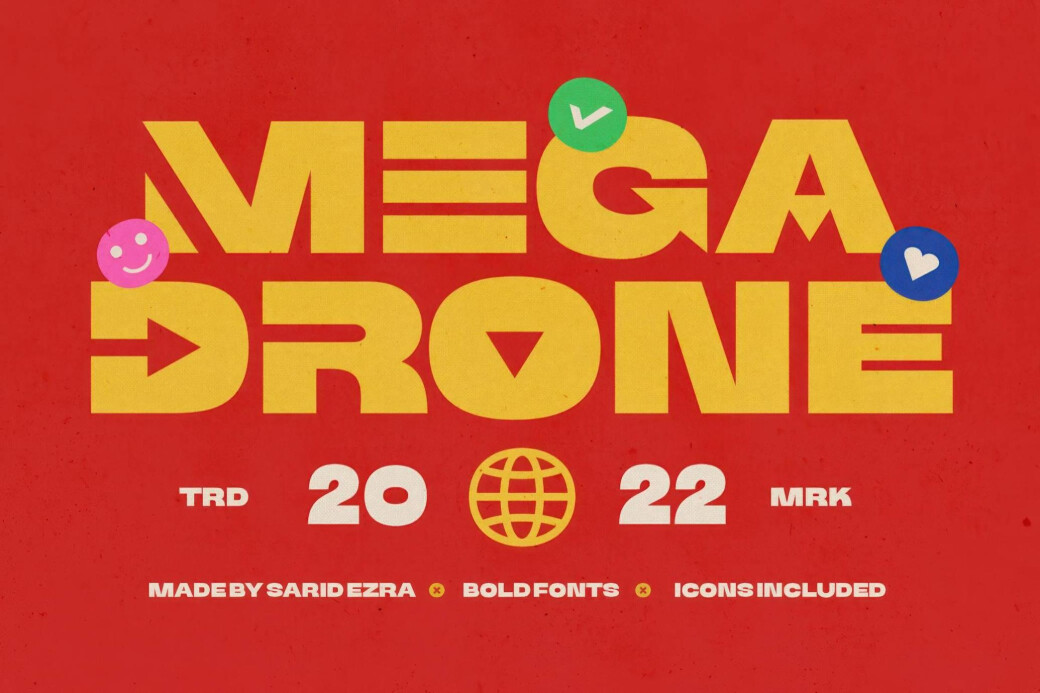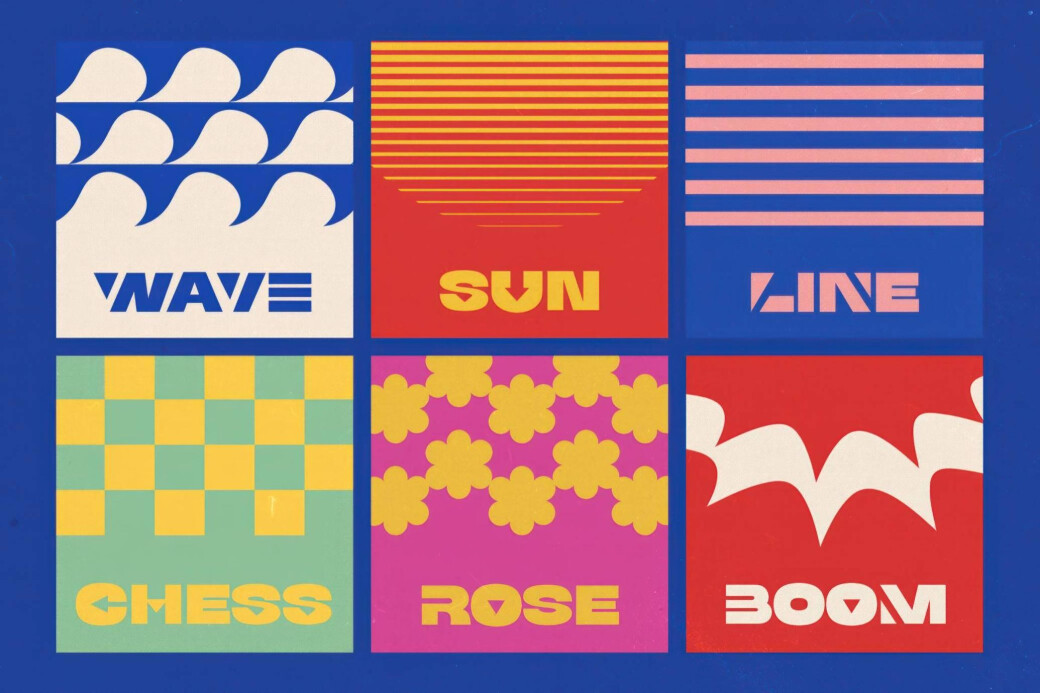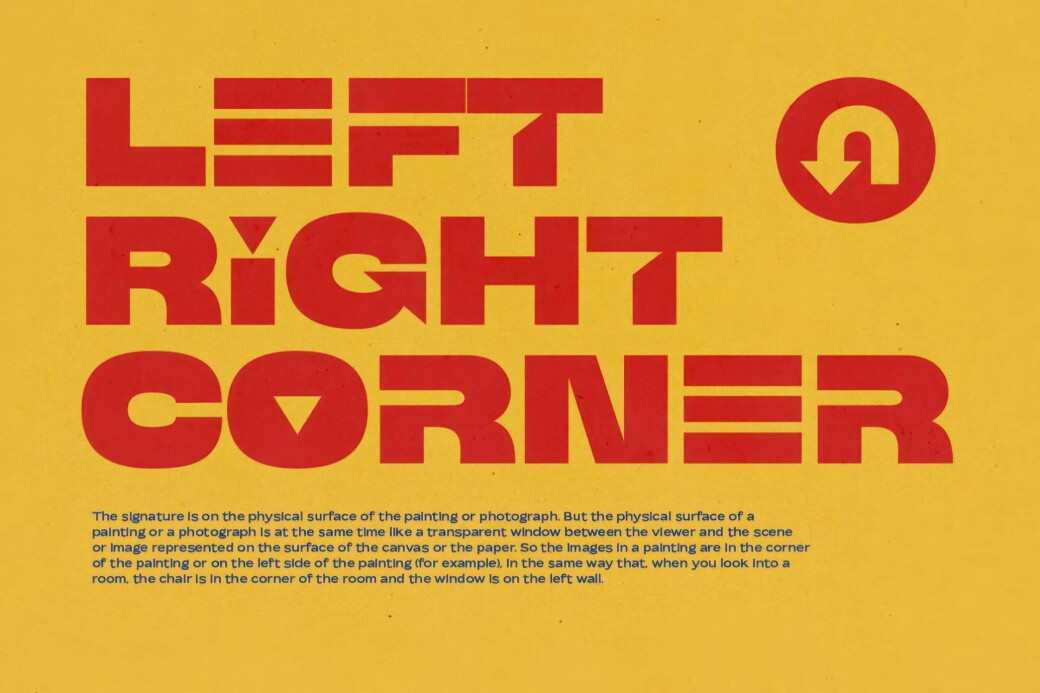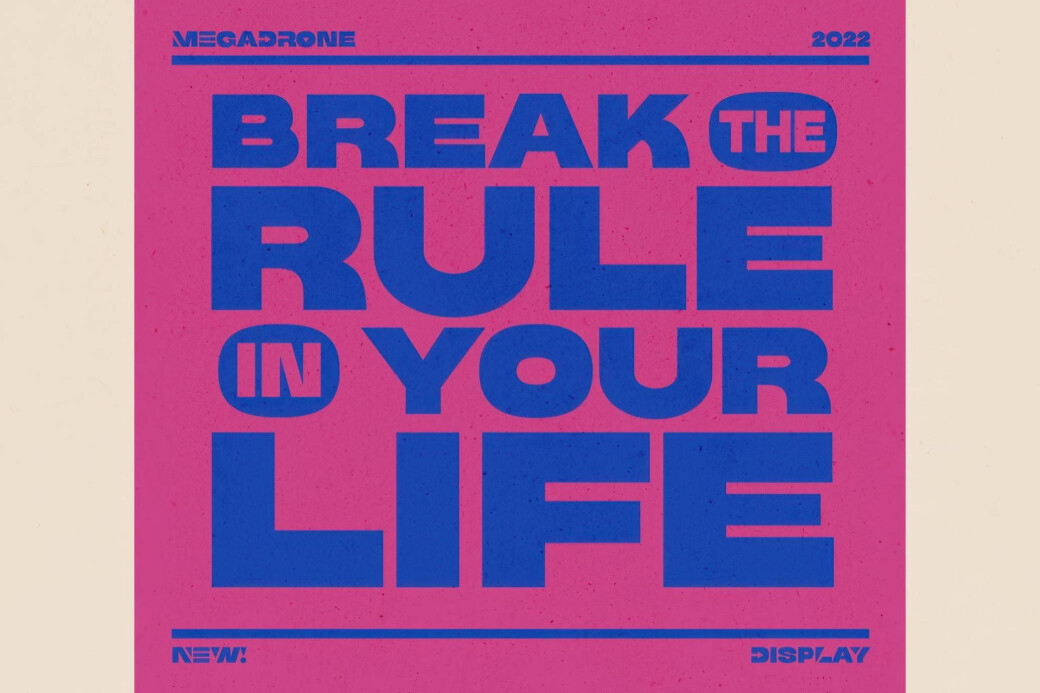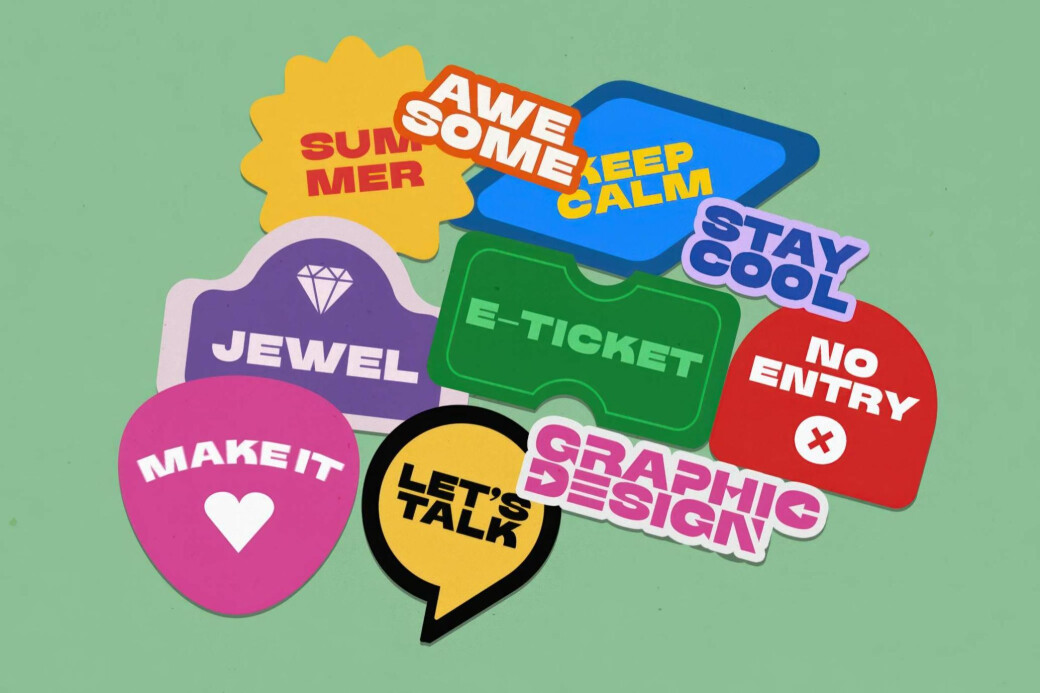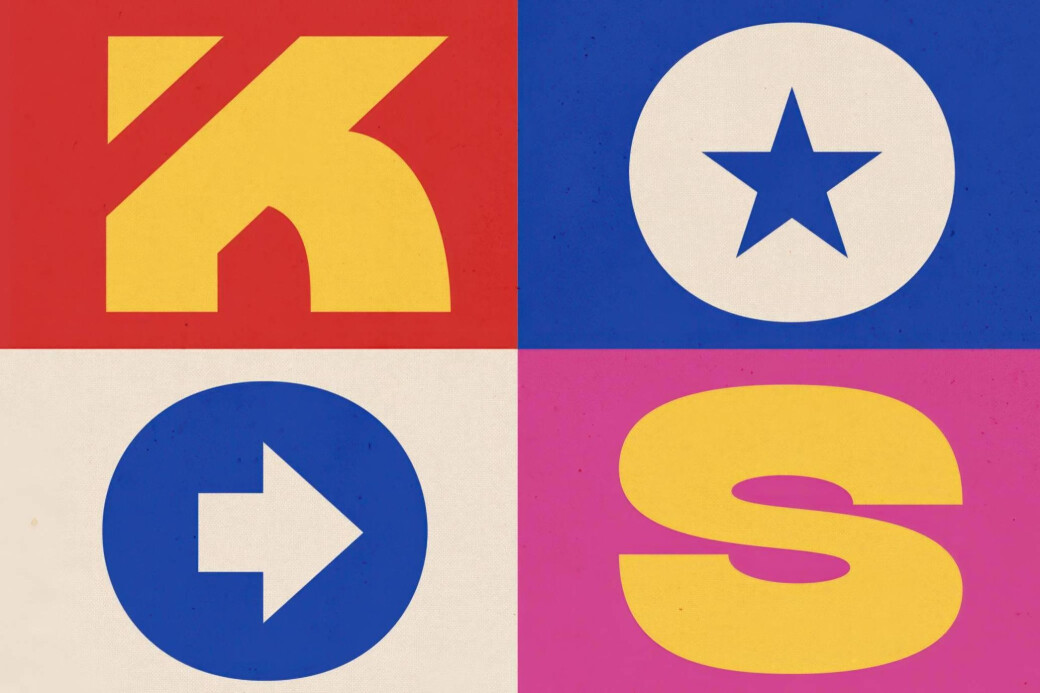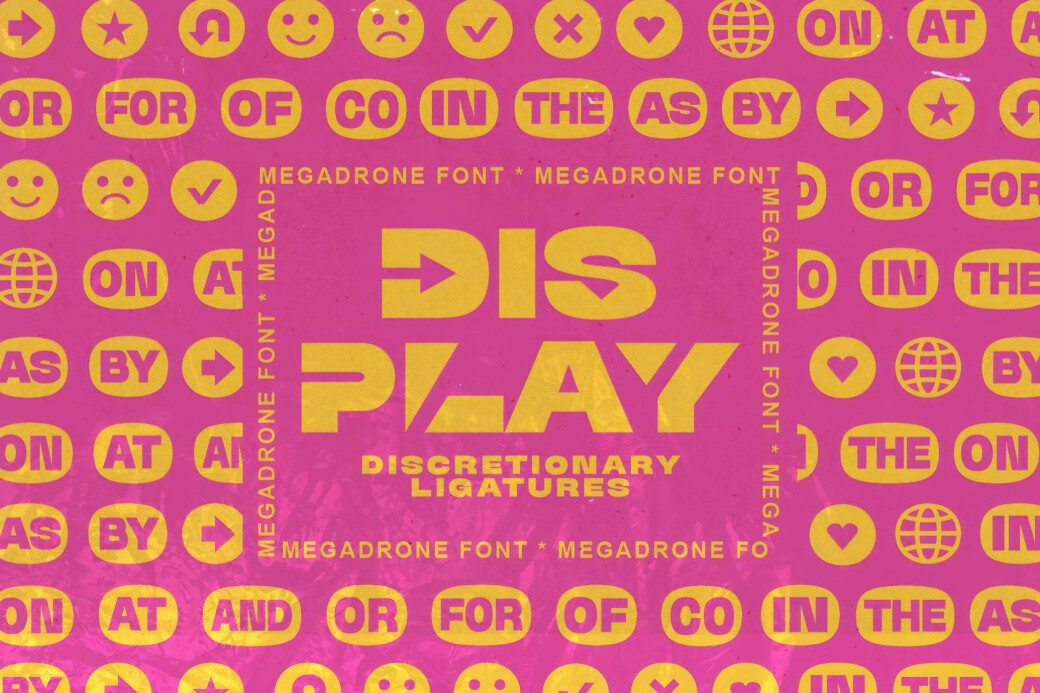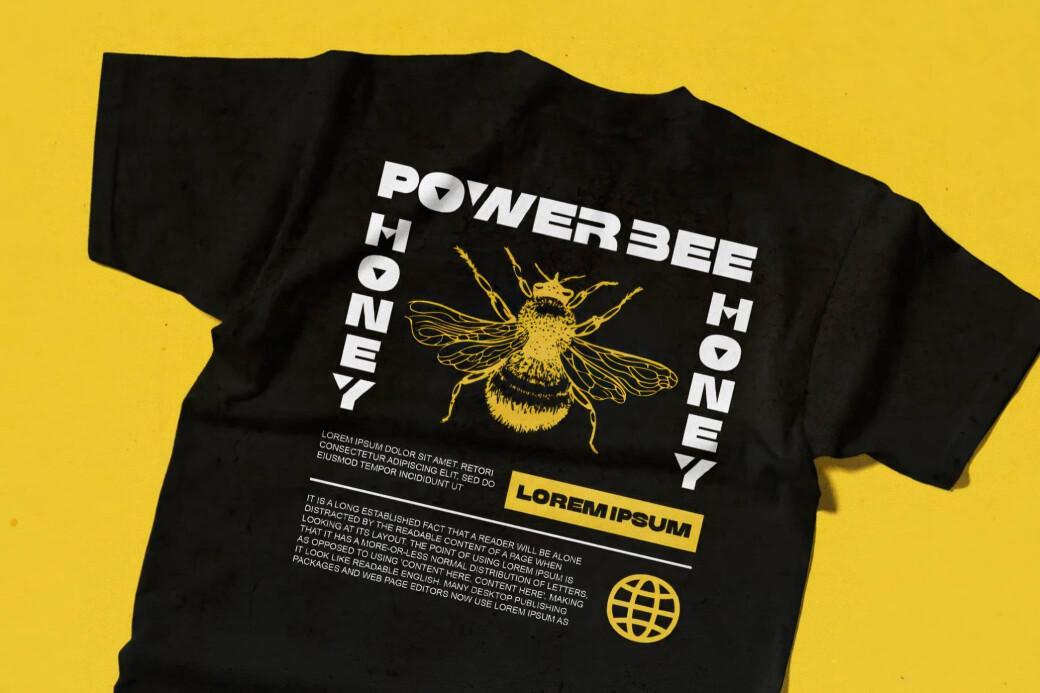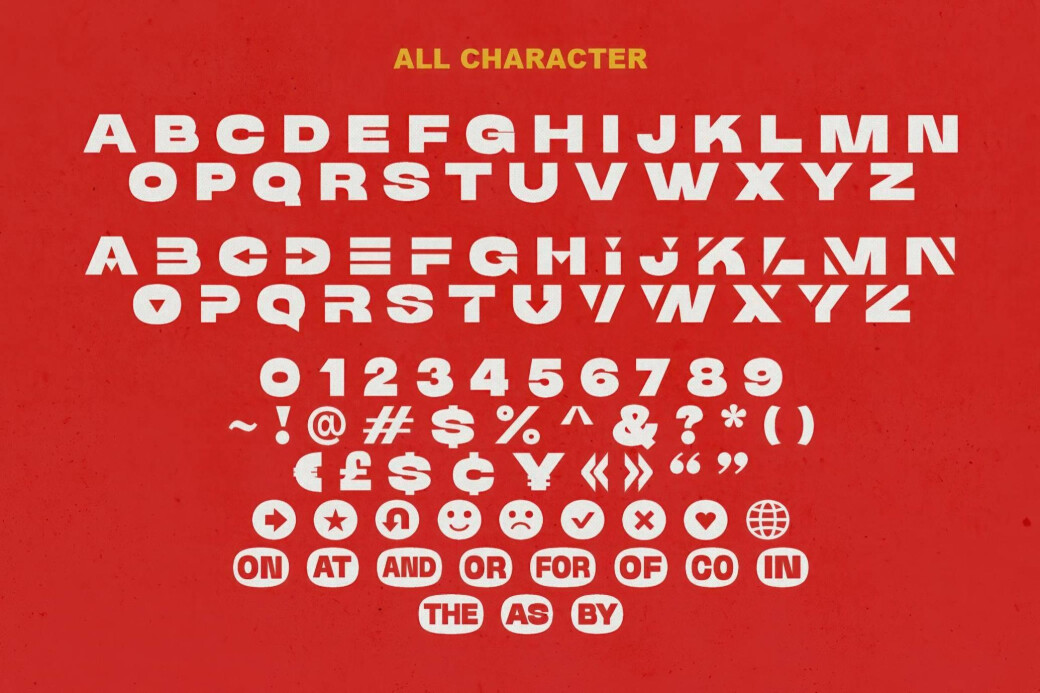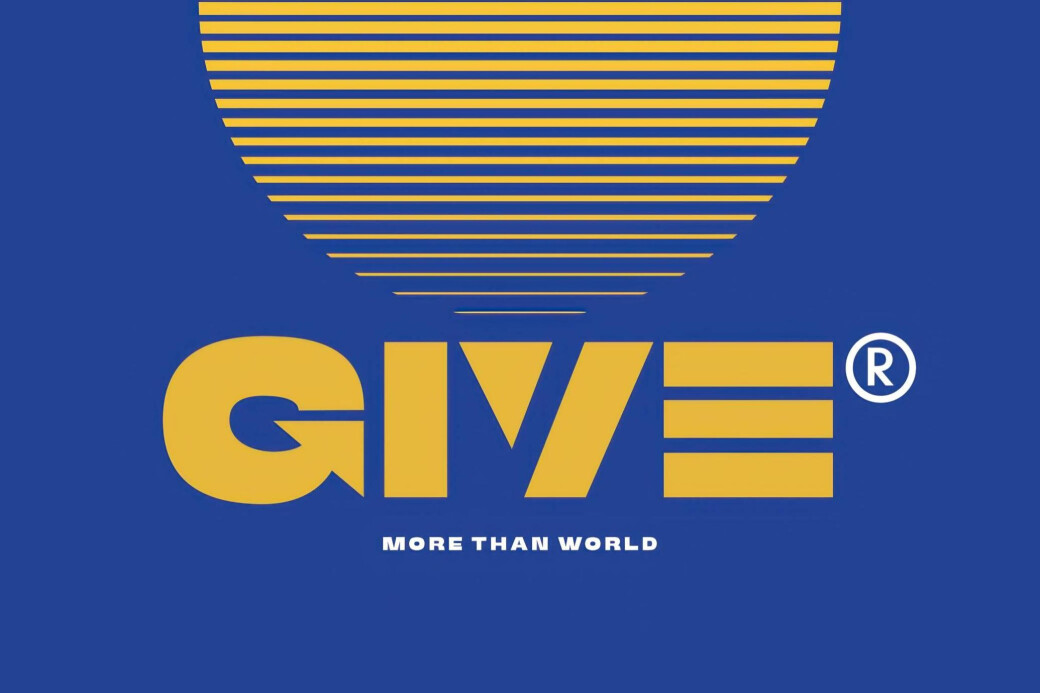
Шрифт Mega Drone словно был создан в кузнице, где каждое слово заковано для того, чтобы доминировать. Его «брутальная» конструкция с большими заглавными буквами непременно привлекает внимание, а возможность использовать строчные буквы добавляет игривый, неожиданный штрих.
— Нужен заголовок, который впечатлит? Mega Drone работает как «молото» — громко, индустриально и невозможно игнорировать.
В наборе глифов можно найти:
— заглавные, строчные альтернативы, знаки препинания, цифры и мультиязычные символы. Иконки и ключевые слова доступны через лигатуры,
что делает создание смелых композиций удивительно простым. Этот шрифт — универсальное «оружие дизайна», созданное для логотипов, постеров и визуалов, которые не хотят «сидеть тихо», так что воспользуйтесь его преимуществами!